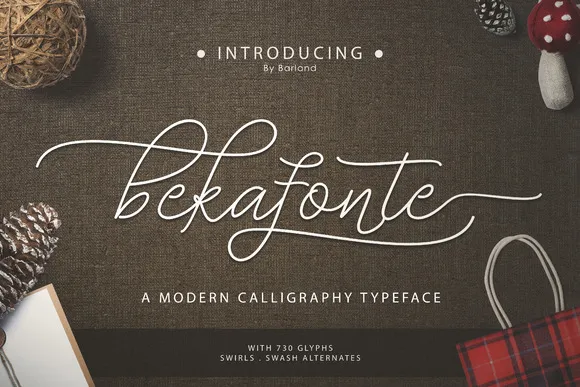
Bekafonte Typeface – Download Grátis
A Bekafonte Typeface é uma delicada tipografia desenhada à mão que traz elementos artísticos sutis para qualquer projeto. Com alternativas e curvas elaboradas, esta fonte manuscrita oferece um toque de frescura e elegância relaxada. Uma escolha perfeita para aqueles projetos onde você quer adicionar um toque único e descontraído. Esta tipografia é ideal para introduzir alegria e sofisticação em seu próximo projeto, seja uma carta personalizada ou uma ilustração de arte digital, ela irá garantir que sua mensagem seja notada. A Bekafonte Typeface é perfeita para designers buscando adicionar um toque criativo à sua produção visual sem abandonar a precisão necessária. Com o designer Barland, esta fonte traz consigo uma rara personalidade única ao seu design, tornando-a ainda mais especial e versátil.
Designer: Barland